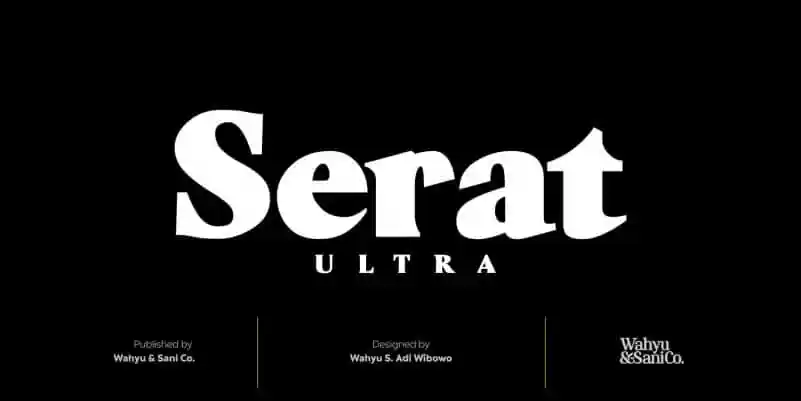
Serat Serif Font – Download Grátis
Introduzimos a Serat Serif Font, uma elegante font serif moderna criada por Wahyu & Sani Co. Este design foi inspirado nos estilos clássicos de tipos que se misturam, com influências diretas das escritas manuscritas do latim no seu início. As minúsculas da Serat Serif Font são versões atualizadas dos Carolingian Minuscules, onde as raízes verticais que tocam a linha de base foram modificadas para ter cortes horizontais, o que torna a aparência mais simples enquanto preserva o estilo do caligrafista nas pontas e na terminação da traçagem. As maiúsculas da Serat Serif Font têm um estilo flare, inspirado nos capitais inscripionais romanos. Esta fonte é perfeita para aplicativos que valorizam elegância clássica em um formato moderno.